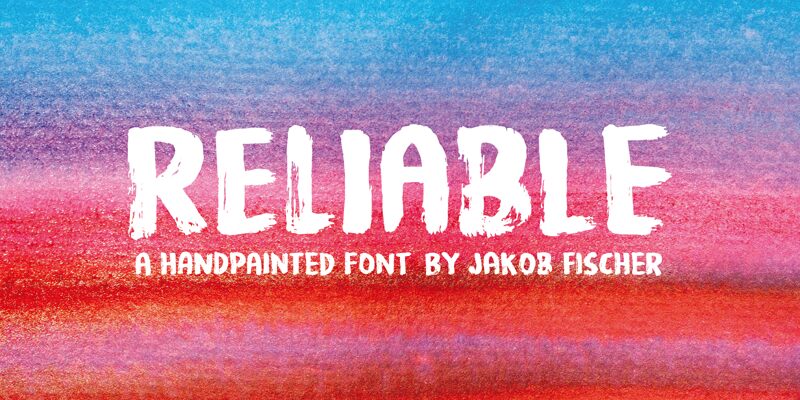
Krój Reliable został narysowany suchym pędzlem, a następnie starannie przekształcony w font. To, co odróżnia Reliable od innych krojów typu brush, to 8 różnych wersji każdej litery! Zmieniają się one automatycznie podczas pisania. Efekt nie jest do końca losowy, ale wygląda bardzo naturalnie. Oczywiście Reliable posiada pełen zestaw znaków diakrytycznych.
Podsumowując: jeśli potrzebujesz świetnego brush fontu, wybierz Reliable!